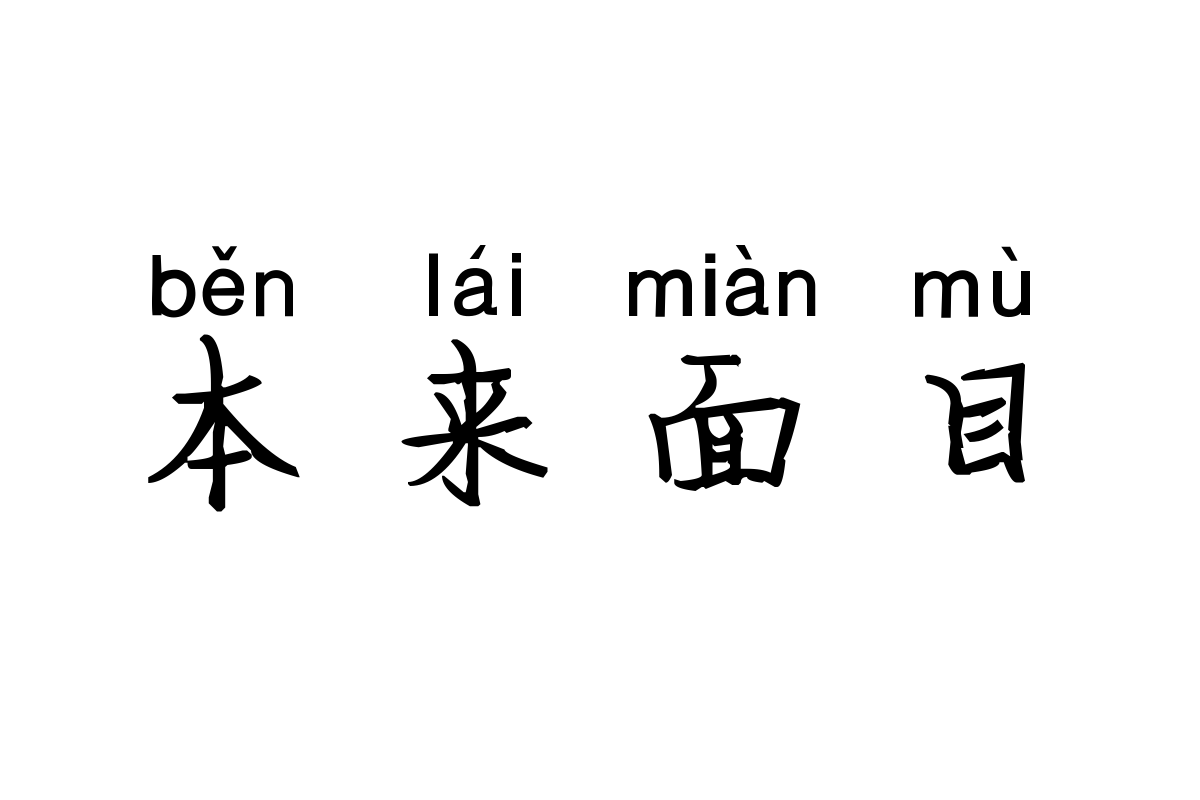
米开柔情物语拼音体是一款具有独特风格的中文字体,它采用了柔和而优雅的设计风格,给人一种温馨、亲切的感觉。这款字体的特点主要体现在以下几个方面:
1. 字形设计:米开柔情物语拼音体在字形上进行了精心的设计,使得每个字都显得圆润饱满,线条流畅自然。这种设计使得整个字体看起来更加美观大方,同时也易于阅读和识别。
2. 风格特点:这款字体的最大特点是其柔和的风格,给人一种温暖、舒适的感觉。同时,它还融入了一些现代元素,使得整体风格更加时尚、前卫。
3. 适用范围:米开柔情物语拼音体适用于各种场合,如广告、海报、书籍、报刊等。无论是用于商业宣传还是个人创作,这款字体都能展现出独特的魅力。
总之,米开柔情物语拼音体是一款具有独特风格的中文字体,它以其柔和的设计风格和优美的字形赢得了众多用户的喜爱。无论你是从事设计工作还是个人爱好者,都可以选择这款字体来提升你的设计作品的品质。